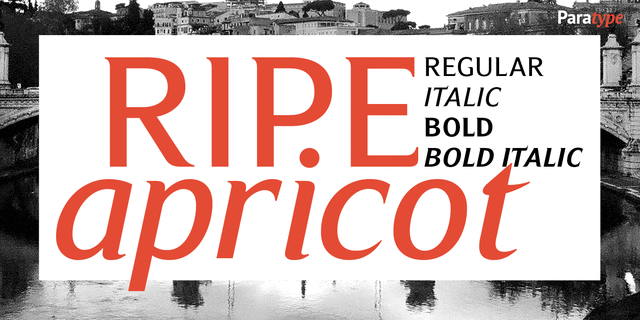
Шрифт Ripe Apricot (Зрелый Абрикос) представляет собой акцидентный гротеск с небольшими односторонними засечками. Его автором является Манвел Шмавонян — один из наиболее известных и титулованных современных армянских дизайнеров. Манвел дал своему шрифту название, которое не столько ассоциируется с формой знаков, сколько связано с тем фактом, что работа была закончена к моменту, когда в Армении созрели абрикосы. Гарнитура состоит из четырех стандартных начертаний и рекомендуется для набора небольших текстов, рекламной продукции, вывесок. Шрифт также может использоваться в журнальном и Веб дизайне. Шрифт выпущен компанией ПараТайп в 2010 году.